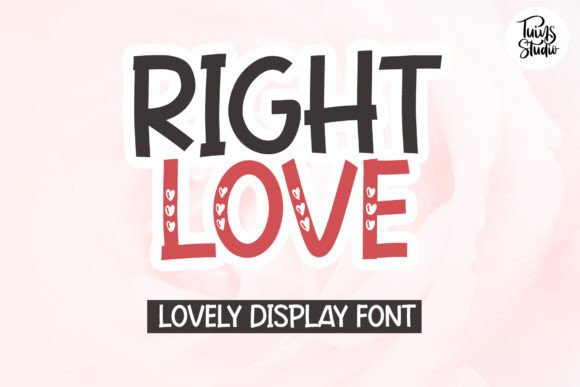
Right Love
適切なデザイン要素を見つけるのは難しい場合がありますが、Right Loveは作品を即座に引き立てる優れたコレクションを提供します。
POD(オンデマンド印刷)製品、結婚式の招待状、またはソーシャルメディアのグラフィックを作成している場合でも、Right Loveは理想的です。